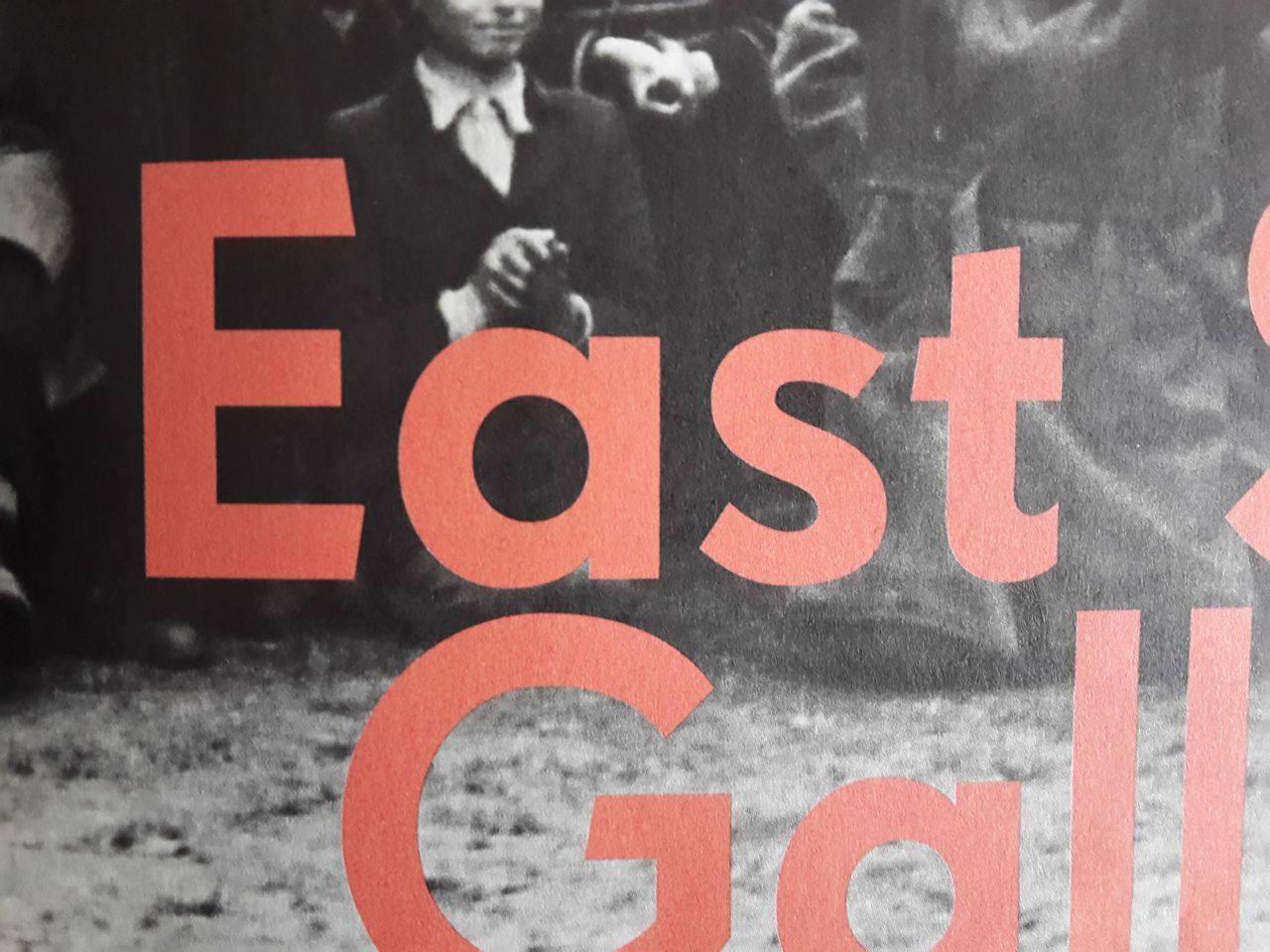
Hilfe, Welche Schrift ist das? (Tage des Zorn/11 Freunde)
Haber aber noch eine die ich ziemlich gut finde, die Typo ist aus dem 11 Freunde Magazin.
Also die Gotham ist es doch nicht, die Schrift sieht ihr aber total ähnlich. Beim E und T sind die Buchstaben minimal angeschrägt
Ich denke hier wurden mehrere geometrische Fonts gemixt. Ralfs Vorschlag dürfte schon stimmen für Deine obere Abbildung. Unten ist auch ein anderes, einfaches a enthalten.
Ja stimmt :D Aber die Typo ist auch interessant, da würde ich auch gern wissen welche das ist hehe
Wie schon in deinem zweiten thread zu diesem Bild: